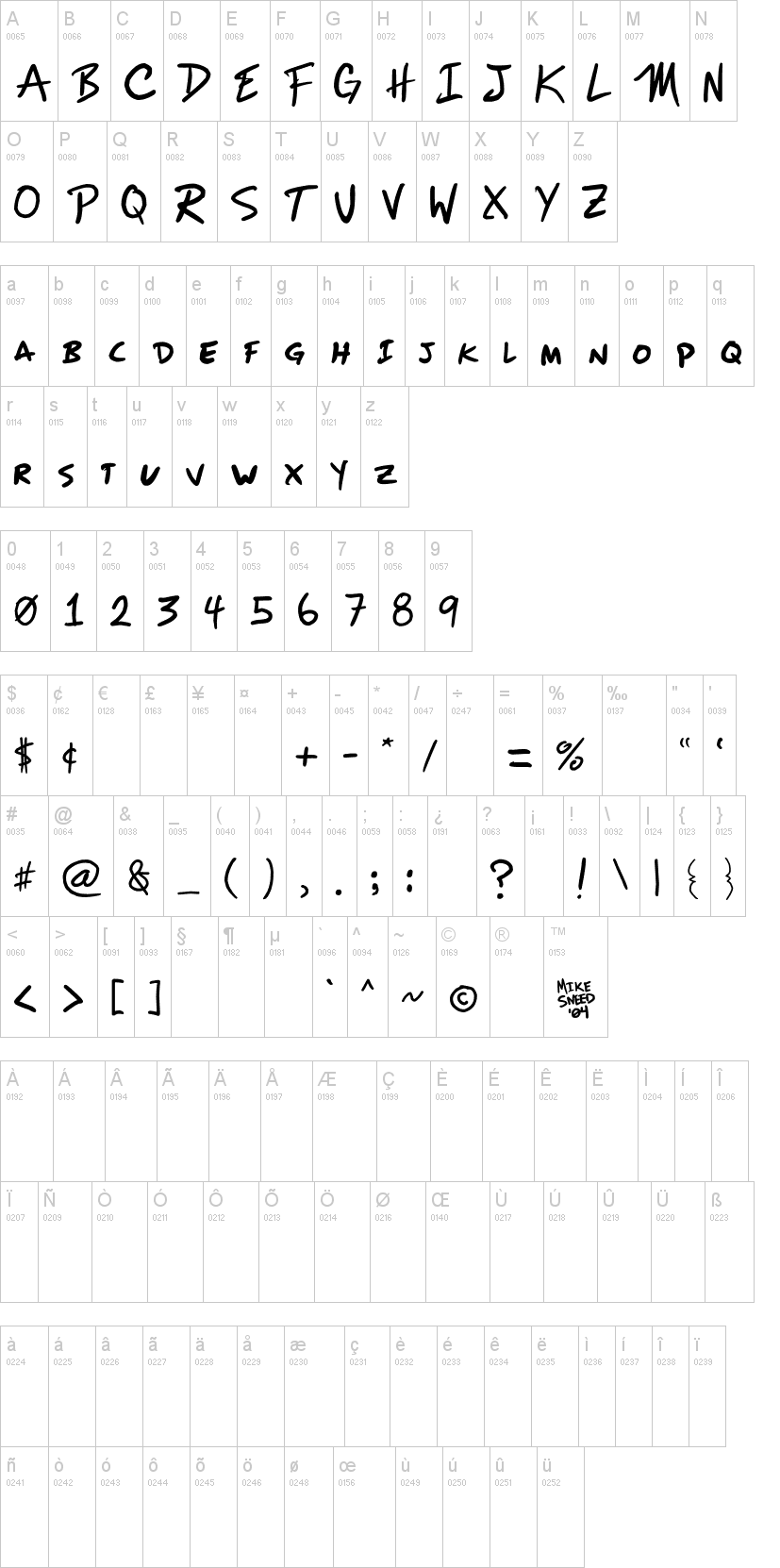
Mizike
Mizike 是一款简洁时尚的字体,由著名设计师Mizike 创作。Mizike 字体完美地结合了现代感和传统感,拥有简洁而清新的外观,适用于品牌标识、广告标语、海报、海报等设计项目。Mizike 字体拥有丰富的字体样式,其中包括细体、粗体、斜体、带圆角等,可以满足不同的设计需求。Mizike 字体具有极佳的可读性,能够让文字更加清晰易读,让设计更加精致。
Mizike是一款非常不错的手写艺术字体,具有很好的视觉感,适合于文化类的宣传设计、商业类品牌的广告和产品包装设计以及个性化文字排版等较多场景。